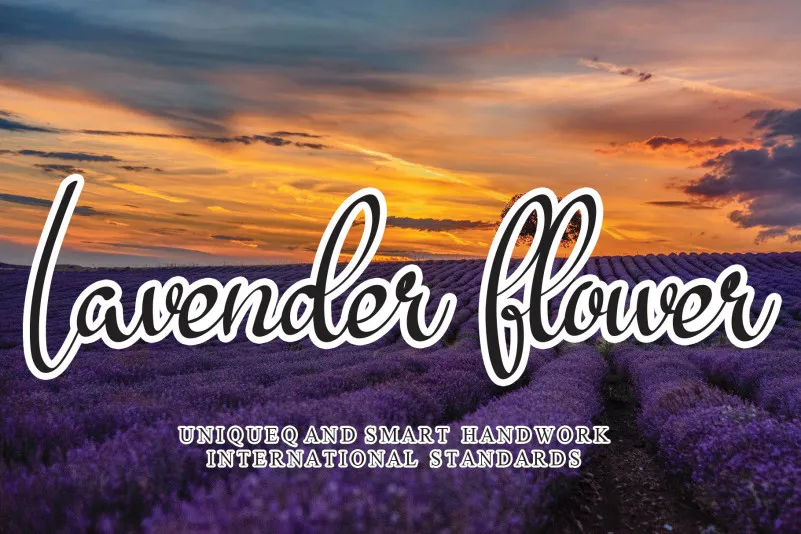
A Lavender Flower Script Font é uma deliciosa e elegante tipografia feita à mão. Suas letras distintas e bem arredondadas a tornam um verdadeiro espetáculo de design. Esta fonte traz consigo sua versatilidade incomparável, permitindo-lhe criar designs memoráveis. Perfeito para aqueles que desejam dar um toque delicado e elegante aos seus projetos, esta fonte é definitivamente uma escolha inspiradora. Crie o seu próximo design de forma única com a Lavender Flower Script Font.